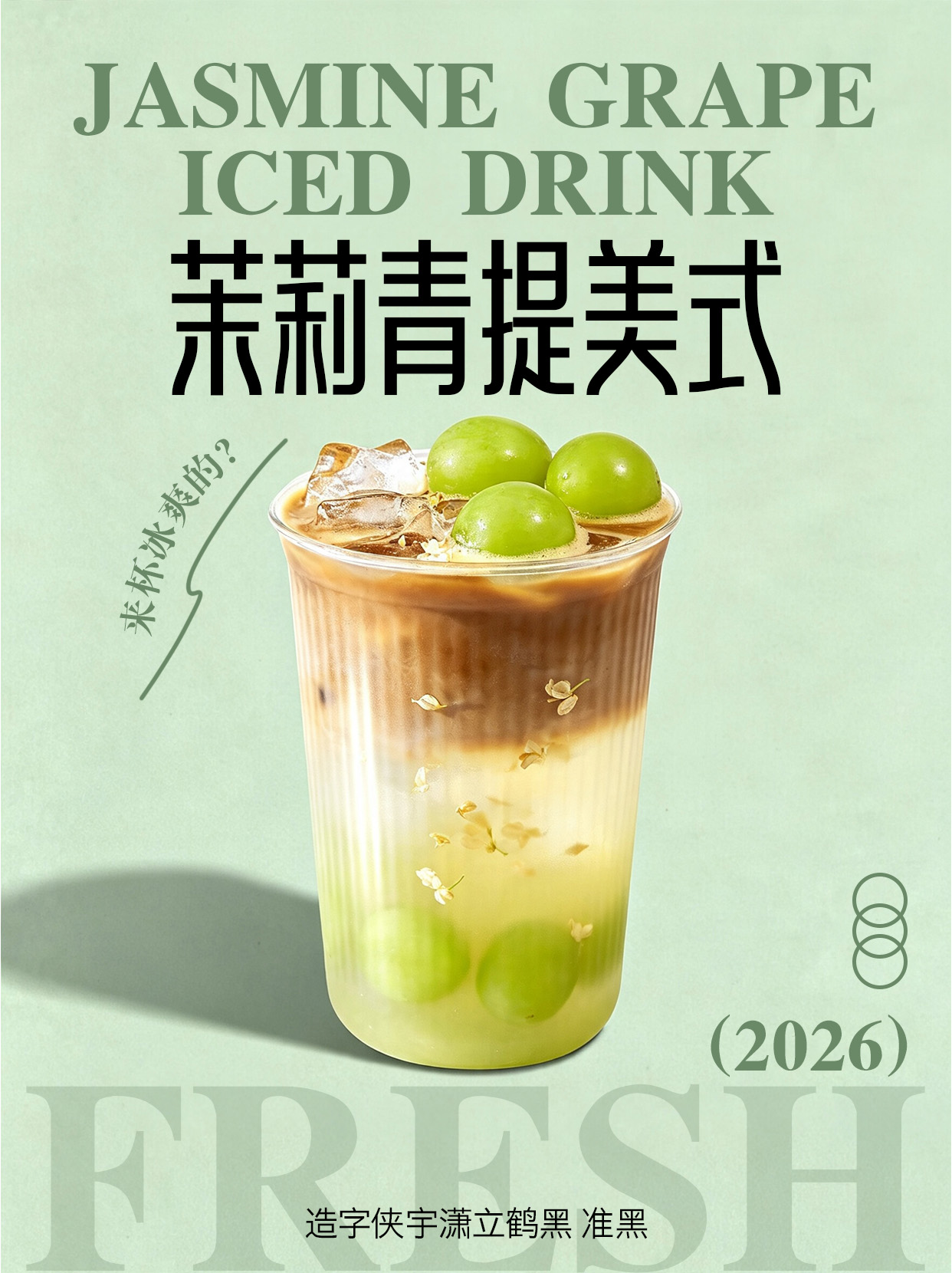
造字侠宇潇立鹤黑 准黑
野鹤纷飞,日暮不思归
造字侠宇潇立鹤黑是一款优雅现代、修长挺拔的创意黑体。结构方正高挑、外轮廓棱角硬朗,内部留白均匀,笔画转角温润柔和,使笔画在保持黑体简洁利落的基础上,呈现出柔和温润之感,仿若墨迹在纸上自然流淌,赋予字体一种呼吸感与生命力。字体包含从标题到内文总共六级字重,适合用于运动品牌、国潮文创、影视游戏、文旅展览等多元场景。